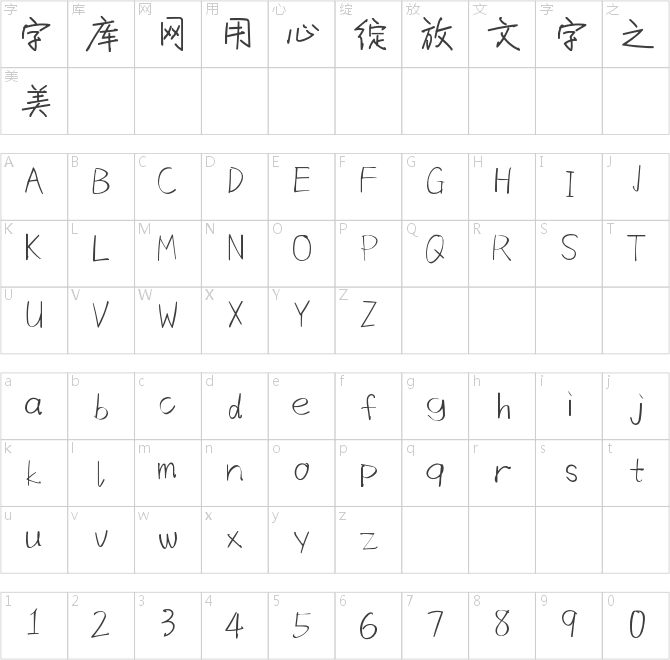
方正
剎那永恒字體下載FZSJ-SHANYH
剎那永恒體,這款字體筆畫遒勁舒展,張弛有度,字形左右延伸,重心平穩(wěn),結(jié)構(gòu)典雅自然,風(fēng)度翩翩,文藝氣息濃厚。適用于文藝類的書刊、品牌廣告和產(chǎn)品包裝設(shè)計,綜藝影視用字,以及社交網(wǎng)絡(luò)的個性化用字。
剎那永恒字體FZSJ-SHANYH字庫是一款讓人賞心悅目、百看不厭的中文字體,適合各類廣告和產(chǎn)品包裝設(shè)計應(yīng)用,字體大小4.05MB,格式為TTF字體,上傳用戶是lackbbay,作者/版權(quán)方為方正手跡